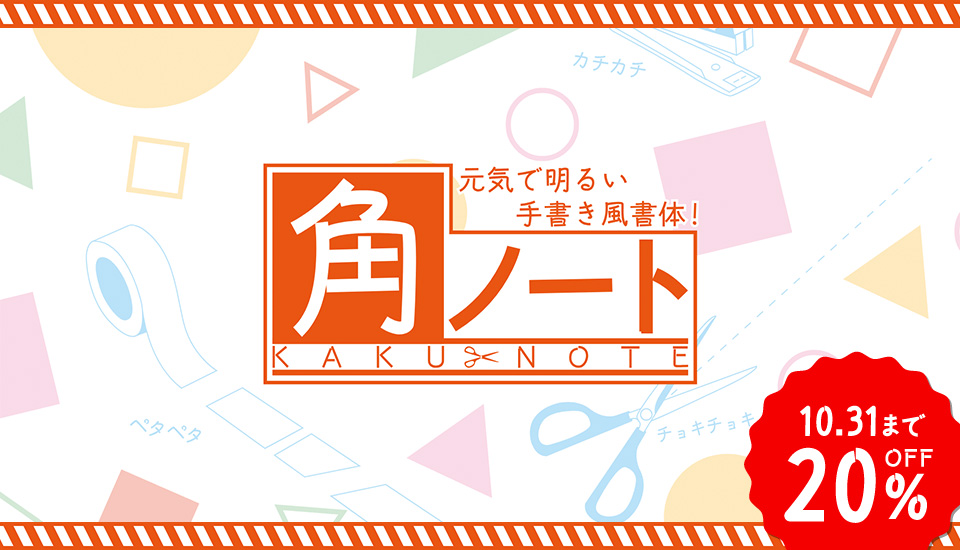
元気で明るい表情の手書き風書体『角ノート』が登場!
永年にわたる書体開発の歴史の中で「可読性の良さ」と「文字の美しさ」を変わらず追求する老舗フォントメーカー『モトヤ』から、手書き風書体の第3弾として「モトヤ角ノート4/6」が登場しました。その特徴やモトヤノートとの比較、デザインのこだわりについて紹介していきます。
モトヤ角ノートとは
モトヤ角ノートは、2018年に登場したモトヤノートの骨格を利用したバリエーション書体の一つです。モトヤノートが持っている柔らかさや優しさに対して、モトヤ角ノートでは始筆と終筆に角ができることによって生じる輪郭同士の隙間を活かして、子供のような無邪気さや、元気でハキハキとした明るい表情を持たせています。
印刷物における小見出し・中見出しをはじめ、テレビテロップなどのデジタル分野でも幅広く活用できます。
モトヤノートとの比較
書体の特徴
手書きならではの筆法をモトヤノートから継承。ウェイト展開はモトヤノートよりも一段階太めの W4/6 となっています。
文章全体の表情に遊び心を持たせ、元気で明るい表現が可能となっています。
ウェイト展開
遊び心を持った元気で明るい表現
使用例
印刷物やWebの見出しやPOP、テレビやYouTubeなどの動画テロップにオススメです。
書体見本